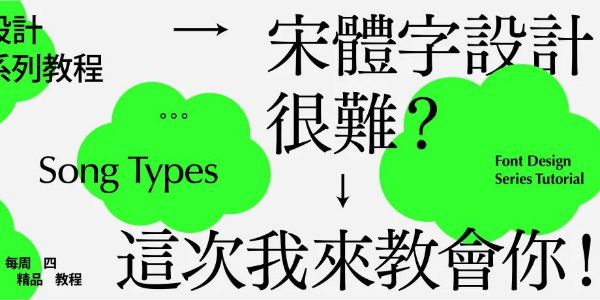
宋体字设计很难?这次我来教会你!
大家好,我是千树。今天这节课我将和大家聊一聊设计宋体字的一些内容。宋体字可以说是我们现在最常用的字体之一,一方面他与黑体一样,具有非常良好的可读性和易辨性,另一方面,他又比黑体更具有历史感和东方韵味,我们可以看到很多的教材、书籍内文或者官方文件,都是用的宋体字,甚至许多设计都会用一些比较有表现力的宋体字作为标题。所以可想而知,学习设计宋体字对我们的帮助有多大。正所谓欲知大道,必先知史。所以在讲如何设计宋体字之前,我们先来扒一扒宋体字的历史吧。
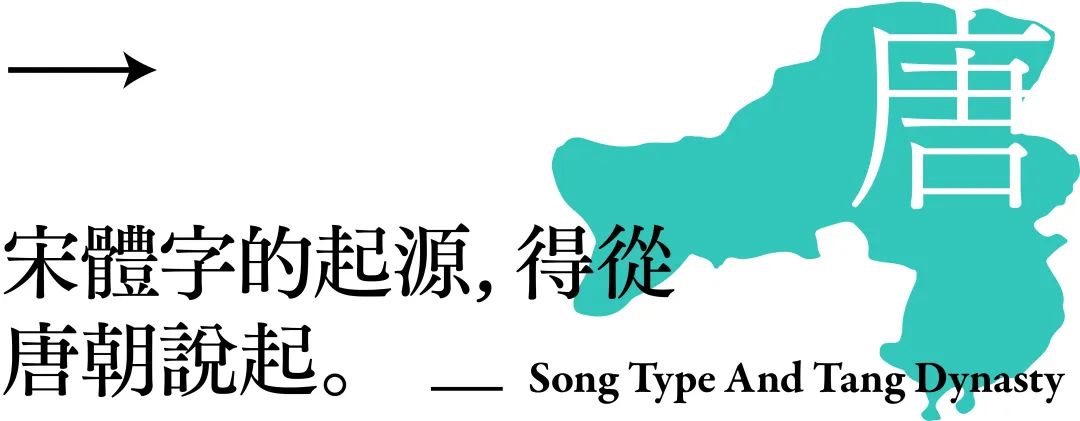
虽然说宋体字叫做宋体字,但是如果要追溯宋体字的起源,我们还得从唐朝说起。
唐朝时期,佛教在中国开始盛行开来,唐朝皇帝甚至派出唐僧师徒四人前往西天取经。
于是便出现了“抄经生”这种人肉印刷机。这篇经文便是当时唐朝的抄经生所抄写的,他们需要使用规整统一的楷体,文字的开头在同一水平线,而且每一列的字数统一规定为17或者19个字,方便字数的统计,像这一篇经文每一列就是17个字。
可是即便出现了大量的抄经生,依旧满足不了人们对经书的需求。于是聪明的中国人开始印刷经书,将经文刻在木板上,就可以实现大量的印刷了。
可是楷书刻起来是很不方便的。一方面,书法家写的楷书讲究起承转合、抑扬顿挫,不同的人写出来的字风格差异十分明显,例如颜真卿和赵孟頫他们所写的“宋”字就明显不同,即便用笔临摹都很难了,更别说雕刻出来了。
另一方面楷体由于是书写的字体,所以大多数笔画都是带有弧度的,而在木板上刻字,曲线是非常难刻的。
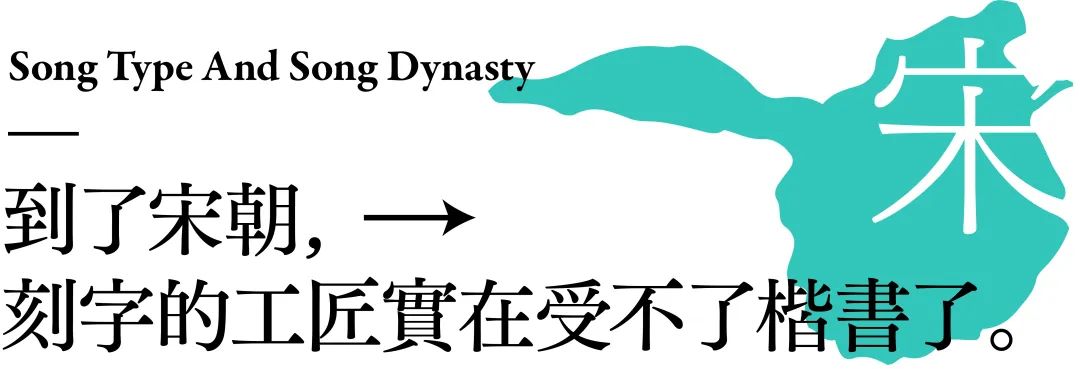
于是他们逐渐将曲线刻成直线,把笔画的弧形特征降低,也将楷体中相同的笔画进行规范了,这样的字体便是宋体字的前身。
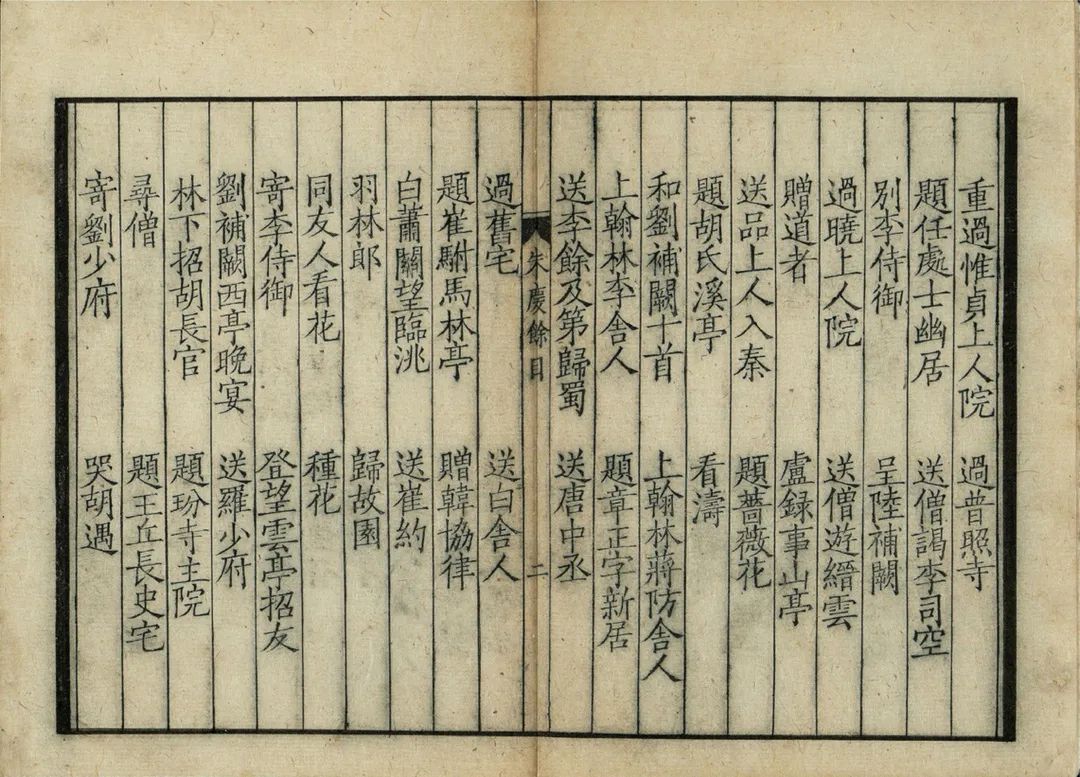
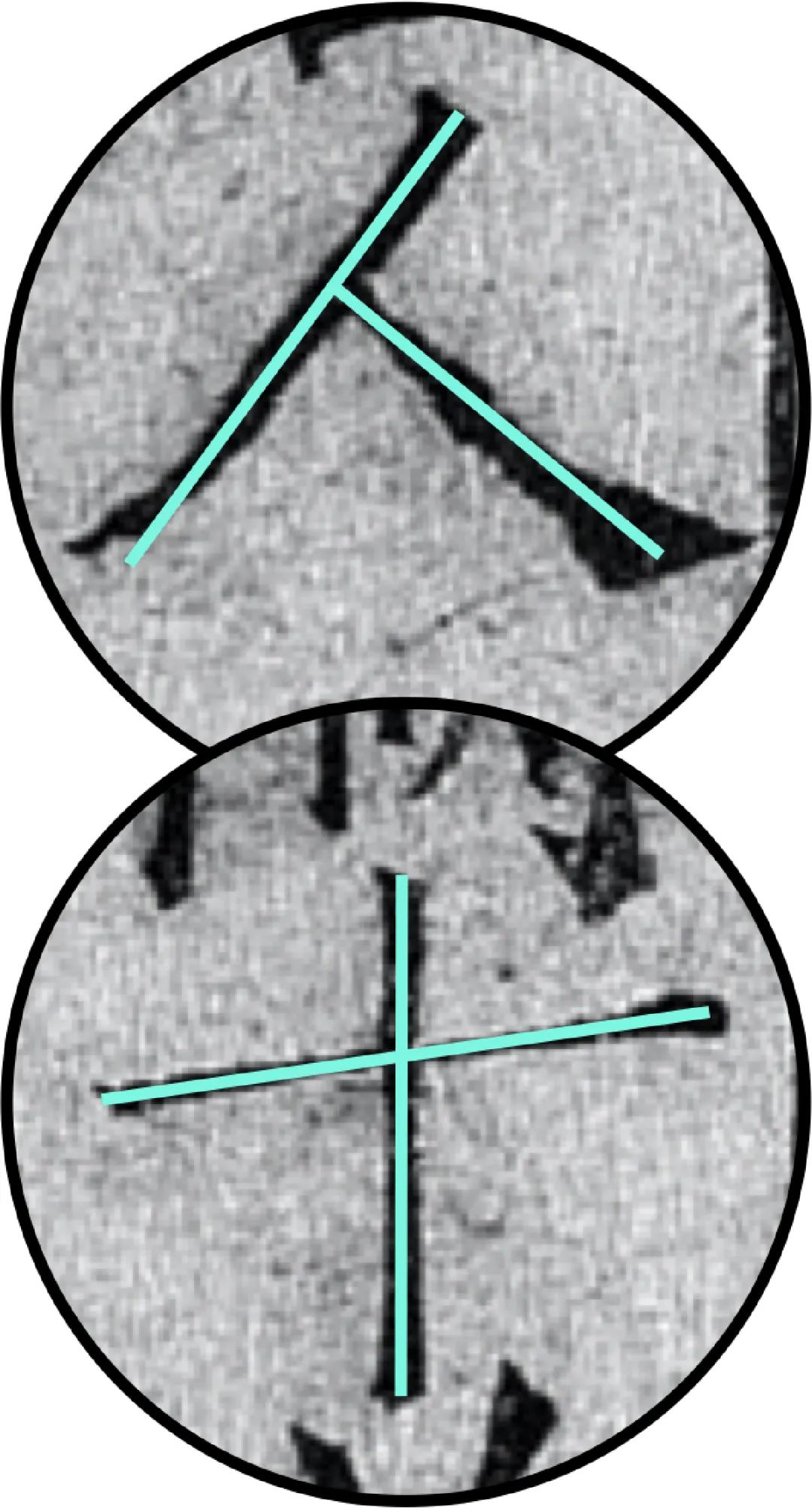
我们可以看一下宋朝时期的刻本,这是南宋时期陈宅经籍铺所刊刻的《朱庆馀诗集》。这时,撇、捺等笔画的弯曲程度大大降低了,而竖笔和横笔也基本上变成笔直的直线了。不过宋朝时期刻本体的横画依旧是倾斜的,从中依然能很明显地看到楷体的痕迹。那么为什么宋体字会形成横细竖粗,横画后带三角形饰角的字形呢?
那是因为刻字的木板上是带有木纹的,如果垂直木头的纹理刻的话,笔画会比较容易断,需要加粗一些。而如果是顺着木纹刻的话,就没那么容易断,所以可以相对细一些。可是为什么是横画细,竖画粗呢?反过来不行吗。
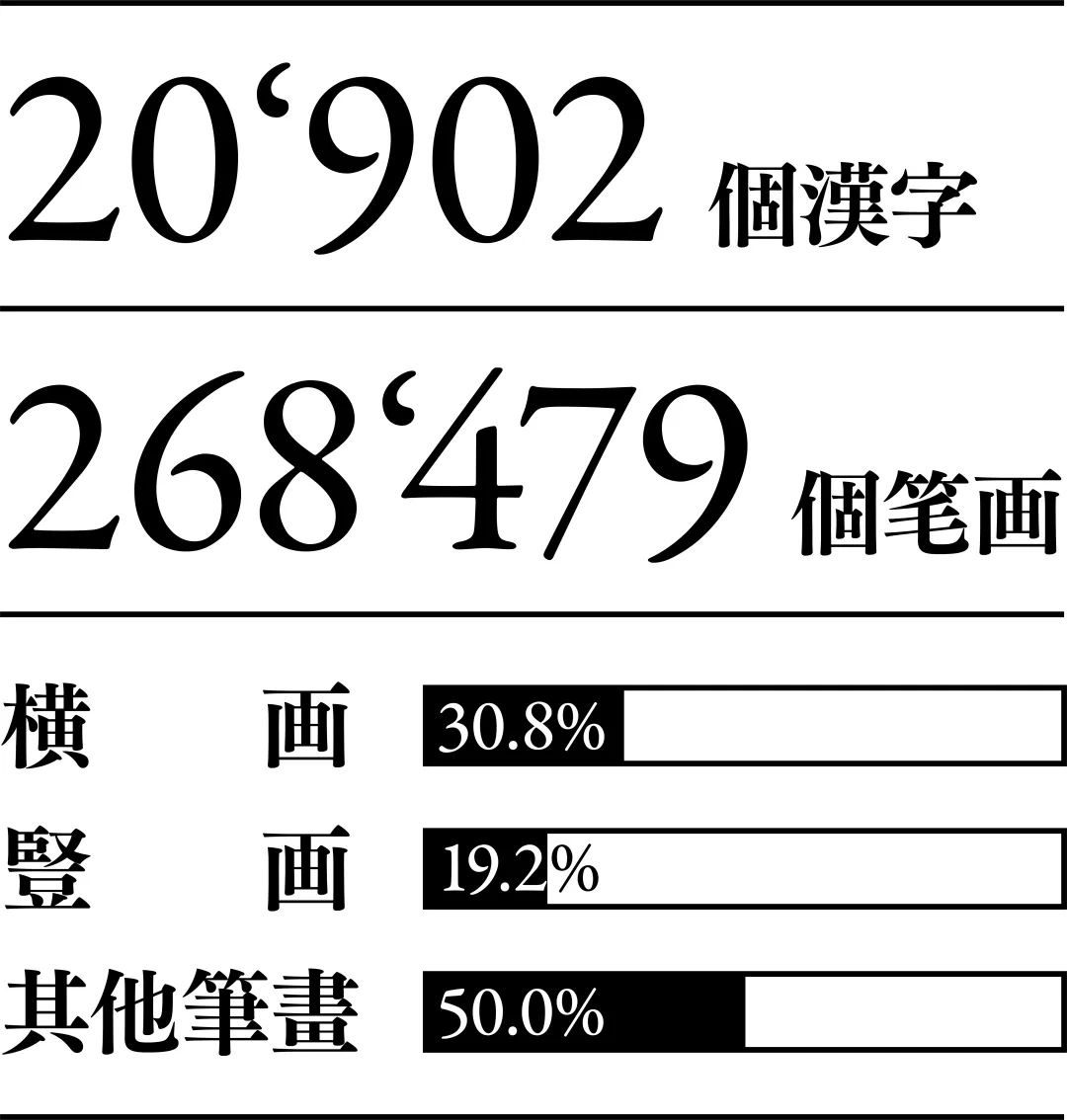
那是因为在大多数的汉字中,横画都是比竖画多的。上海交大的郭曙纶教授对20902个汉字进行了统计,发现这些汉字的总笔画数量多达268479个,而其中横画有82682个,占30.8%,而竖画有51459个,占19.2%。可见,在汉字中横画是比竖画多的。所以如果将横画刻粗,竖画刻细的话,可能会使得字体过挤而不美观。
虽然说横画顺着木纹,比较不容易断,可是横画的两端还是会比较容易磨损的,所以工匠们一般会将横画的两端稍微刻大一些,形成饰角。
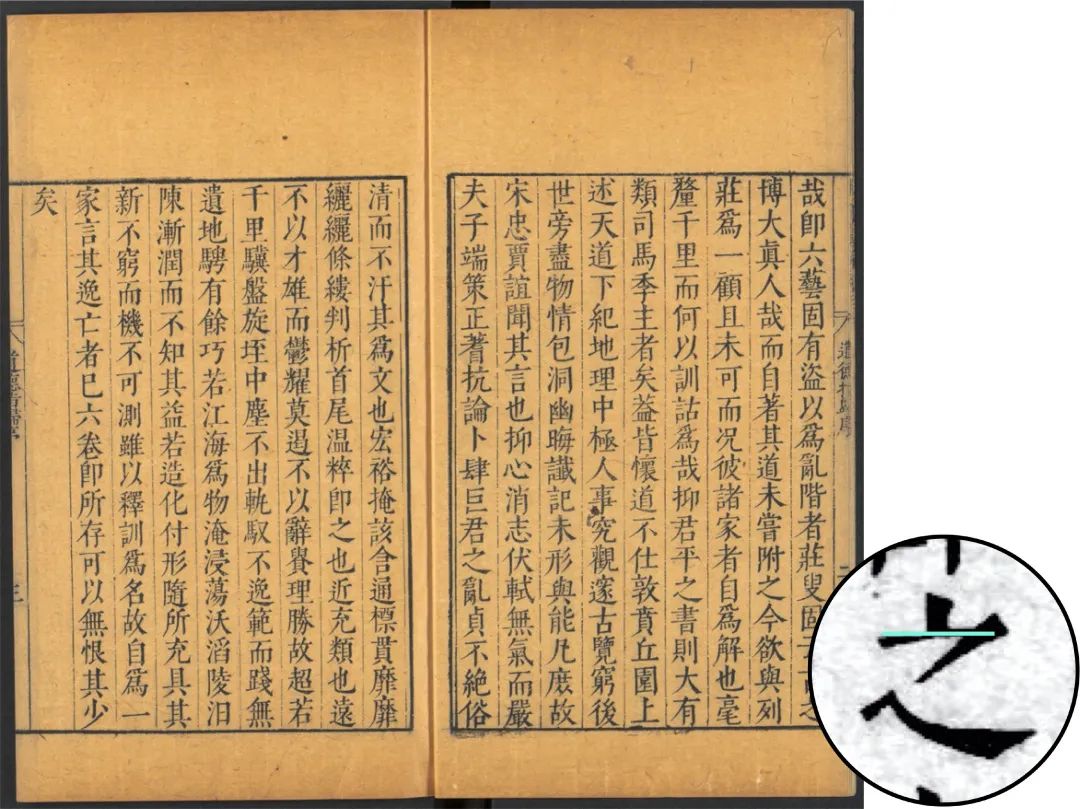
在明朝,宋体得到了进一步的简化,原本复杂精细的刀刻技法简化成了横、竖和斜三种,所以刻字工匠的门槛大大降低了,宋体字得到了真正的普及。我们同样来看一下明朝时期的刻本,这是明朝时期汲古阁刻印的《道德指归论》,这个时候的宋体横画已经基本变成水平了,虽然笔画依旧比较张扬,但是已经少了许多楷体的影子。所以从明朝时期开始的刻本体才能算作真正的宋体。
也是在明朝时期,宋体字传到了日本,所以现在日本将宋体字称为明朝体。
清朝是刻本最多的一个朝代,而宋体字在中国真正被确定统一称为“宋体字”也是发生在清朝。
了解了宋体字的历史后,我们可以发现宋体字的意义并非只是美观和易读而已,他是经过中华民族近千年传承、优化和改良的文化结晶,他的身上有着厚重的文化气息。也难怪中国、日本、韩国等受中华文化影响的国家会对宋体有独特的偏爱。接着我们就正式进入设计宋体字的教程部分,首先我们来了解一下宋体字的主要特征。
从楷体字转变为宋体,主要产生了三个特征,第一个是横平竖直,也就是说横画是水平的,竖画是垂直的。第二个特征是横画比较细,竖画比较粗。第三个特征是笔画上出现了三角形的装饰角。
可是随着字体设计的发展,对于宋体的定义已经越来越模糊了。例如上面的这三种字体,虽然他们不完全满足宋体的特征,可是它们都能算作是宋体。所以我们也不需要对宋体下一个死定义,免得我们在设计字体的时候被定义所束缚住了。
可是仿宋体是不能够算是宋体字的。我们看仿宋体是不是觉得他和宋朝时期的刻本非常像呢?因为仿宋体是在民国时期,丁善之和丁辅之模仿宋刻本所设计出来的字体,所以仿宋体模仿的是宋朝刻本,而非宋体字,那么仿宋体当然也就不能算在宋体的行列里了。
接着我们来分析一下宋体字的气质。由于宋体诞生于明朝,具有非常悠长的历史,而黑体是在民国时期才产生的,所以宋体相对于黑体更能体现传统感、文化感的气质属性。
所以我们做现代风格的设计的时候,可以使用黑体。
而做比较具有传统风格的设计则可以用宋体。当然也并非说宋体就没办法做现代感的设计,通过对宋体体饰和中宫的设计,我们完全可以做出一款现代型的宋体。
先来说一下中宫,我们在之前的教程里说过,中宫越大,越显现代感,而中宫越小,则越有传统感。在宋体里也不例外。
我们再来看看这两个“東”字,很明显也是左边的“東”字更现代一些,而右边的“東”字传统一些。这两个字的区别在于体饰的不同。体饰越少越简洁,宋体就越显现代;体饰越多越复杂,就越显传统。
另外几何形的体饰也会给宋体带来现代感。
而传统宋体字的体饰则是具有手写感的,线条比较圆滑。
根据体饰和中宫的不同,我们可以大致地将宋体分为三大类。中宫小、体饰多且具有手写感的宋体归类为传统型宋体,中宫大、体饰少且为几何体饰的则归类为现代型宋体。而具有一定手写感的体饰,且中宫偏大的宋体,则归类为中间型的宋体。
除了中宫和体饰之外,我们还经常调整笔画粗细去适应宋体字不同的用途。首先我们先来讲讲正文的宋体。一般正文的字号都是比较小的,如果横画过细的话,会使得横画几乎看不见了,而如果横画过粗的话,笔画又会糊在一块了,所以为了让宋体字在小字号下也能清晰的显示,一般横画和竖画的粗细会控制在1:2到1:3左右,最大一般也不会超过1:4。
不过我们设计正文字体的机会还是比较少的,大多数时候我们都是需要设计比较具有张力的标题字。这个时候我们就可以尝试拉大横画和竖画的粗细差距。当横画和竖画的粗细差距非常大的时候,可以产生较强的视觉冲击力。画面中这三款标题宋体,都用了细横画搭配粗竖画。
有时候我们也可以反其道而行之,将横画加粗,让横画与竖画差不多的粗细。这样我们就可以获得一款非常醒目的宋体。这样的宋体有点像比较粗的黑体,既有醒目的特点,也保留了宋体优雅的属性。
当然,具有张力的标题宋体也并非一定要通过控制横竖笔画的粗细来塑造,通过设计一些有张力的体饰,同样可以让宋体字变得具有表现力。设计体饰是设计宋体字非常重要的一个环节,因为宋体字的大多数笔画是存在许多体饰的,我们除了要将体饰设计得好看之外,更重要的是让不同的体饰和谐共存。如果一个宋体字里存在的体饰都风格不一,那么这个宋体字看着就会不伦不类了。下面我就给大家介绍一个我比较常用的,设计宋体字体饰的方法。
在做字之前,我们要先确定我们想要做的字体的气质,是传统的,还是现代的?文艺的还是可爱的?又或者是其他的气质。因为我们前面也说到,体饰和中宫都会影响字体的气质,所以我们必须要确定了气质之后,才能动手去设计字体的中宫和体饰。
另外还要确定字体的用途,需要比较有张力的标题字体,还是需要具备阅读舒适性的正文字体,那我们也能确定文字的笔画粗细。
确定好了风格之后,我们就可以开始设计笔画了。那么我们先来回顾一下,汉字里的八个基本笔画,我们可以先把这八个笔画的体饰特征都设计好了,再去拼凑我们想要的字。
一般来说,我们设计宋体会先从横画开始设计。因为确定了横画之后,体饰的风格、体饰大小、笔画粗细等很多东西就都可以确定了。
其实宋体中的体饰都是来源于书法中的顿笔,所以我们来看看书法中,横画是怎么写的,书法中的横在起笔和收笔处分别有一个顿笔。这两个顿笔分别对应着宋体横画首尾的两处体饰。对于宋体字来说,横画末尾的这个体饰是非常重要的,他对整个字体的气质影响非常的大。
我们前面已经介绍了这两种衬角分别具有现代感和传统感。
而这一个的衬角是一个比较圆润的圆形,他可以用来做比较可爱的宋体。
这一个衬角和刚刚的就正好相反,非常的非常尖锐,适合用来做比较恐怖的宋体。
还有一点要注意的是,如果竖画越粗的话,横画的衬角一般也要相应的变大一些。
因为宋体的横画本来就已经很细了,如果衬角还非常小的话,横画很容易就会被忽略掉了,横画末端的这个三角形起到了一定强调横线的作用。当然如果是故意要设计成小衬角或者无衬角的话就另当别论了。
横画做好之后,就可以开始设计竖画了。在书法中,竖画在起笔处会有一个顿笔,而收笔的地方会稍微往左侧偏一些,这样分别形成了宋体中竖画起笔和收笔的两处体饰。
那么我们应该怎么用横画推导出竖画呢?横画和竖画关联度最大的地方在横画三角形衬角和竖画上方衬角的这个地方。例如这一组都是直线加切角。
而这组都是曲线加圆角。
另外我们还能将这两个地方给联系起来,因为他们都是起笔的位置。如果横画的起笔是水平的话,那么竖画的起笔就应该是垂直的。
而如果横画的起笔是往外扩的话,那么竖画的起笔也可以往外扩张。
我一般还会将竖画的起笔和收笔的的地方关联起来,如果起笔是垂直的,那么收笔我也会设置成垂直的。
而如果起笔往外扩的话,那么收笔我也会往外扩形成书写曲线,这样整个竖画能看起来平衡一些。
接着来设计横折。书法中在这个转折的地方会有一个顿笔。所以在宋体的横折处也会形成一个装饰角。
其实横折这个笔画在设计好横画和竖画之后基本就已经出来了。只要将他们组合在一起,然后将横画的衬角往回缩小一些,横折就做好了。
讲完了横折我们顺便也讲一下这种口字的结构好了。口字结构由刚刚做好的横折加上一个竖线和一个去掉三角衬角的横线组成。然后我们需要做一些细微的调整。竖笔体饰的这个地方需要往上收一些,不要漏出来,这样的笔画看着能干净一些。
然后竖画入笔的地方也要往上提一些,让左右两边的体饰能够平衡。
最后加上横画,把衬角的部分裁去,注意两个竖线需要出头一些。这个口字就完成了。
然后来做撇和捺。书法里的撇起笔的地方有一个顿笔,所以宋体里,撇有一处体饰。
书法里捺则在起笔和收笔处各有一处转折。所以宋体里,捺则有两处体饰。
撇基本上可以从竖线轻易地推导出来,因为他们的起笔都是一样的,只要稍微调整一下起笔的角度就可以了。
而捺与撇是正好相反的,起笔细,收笔粗,所以捺的起笔需要缩小一些,但是需要保证这两个地方是相同的。而捺的收笔是一个比较独立的地方,只需要风格保持大致一致就好了。
然后将重心往下压,因为重心靠下的字体会显得比较憨一些,那么我们这一组字就完成了。
最后我们用这个字来做一个版面,先建立一个单曲封面125mm*125mm的画板,并设置5mm的页边距和7*7的网格。
然后我们放入一张猫的照片作为版面的主体,占据右下角的5.5栏。
接着我们将做好的字体放在左上角,和右下角的猫做对角线的呼应,可是这么摆放好像还是不够好玩。
所以我们加入英文和线条做成一个文字组合。
最后在版面的左下角加入其它信息,这个单曲封面就做好了。
效果还不错吧。
最后我们来总结一下这节课吧。首先我们给大家扒了一下宋体字的历史,知道了宋体字诞生于明朝,可是最早能够追溯到唐朝。接着分析了宋体字的特征和气质,宋体字相较黑体字具有传统、文化的属性,可是也能通过对体饰、中宫的控制,设计出具有现代感的宋体。然后我们教给了大家一套设计宋体字体饰的方法,最后是四个增加宋体字张力的常用手法。那么我们这节课就到这里,我是千树,我们下次再见。